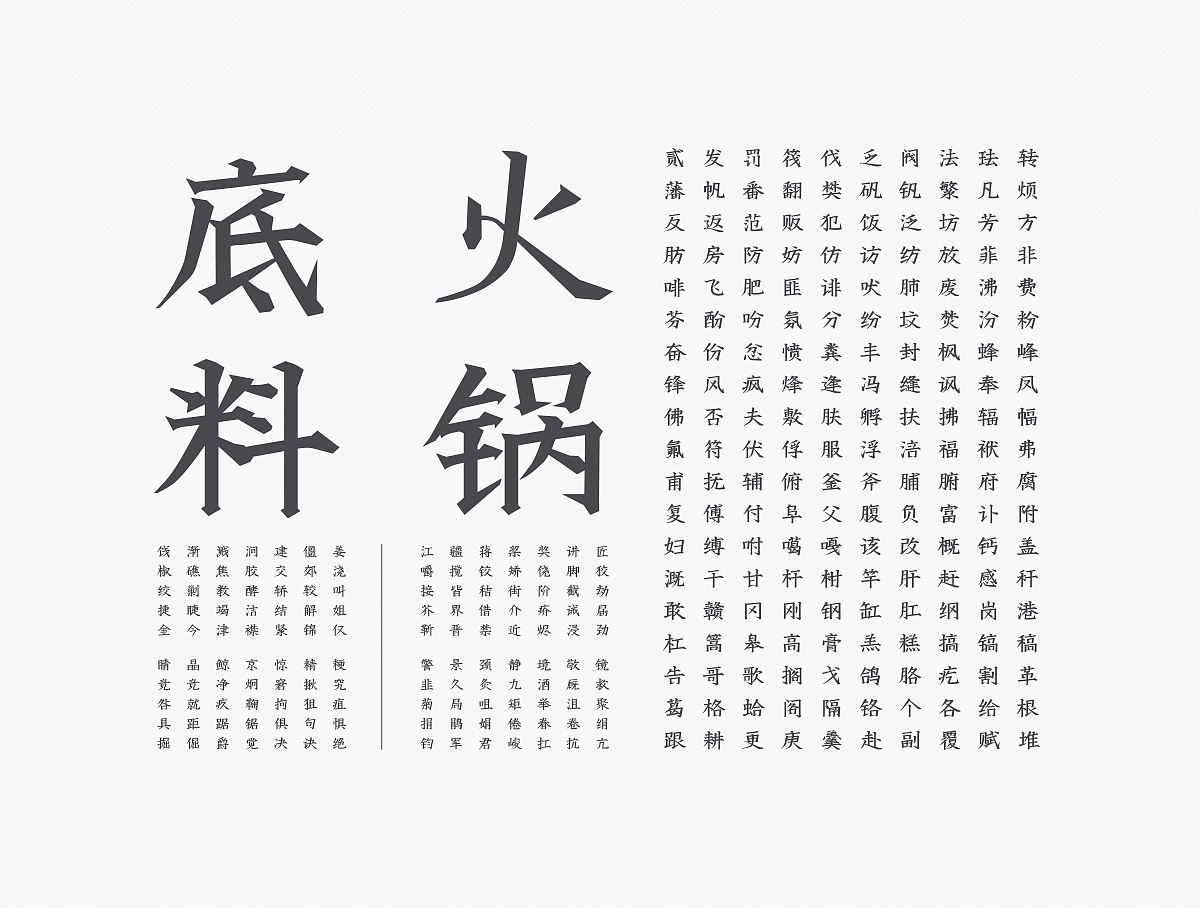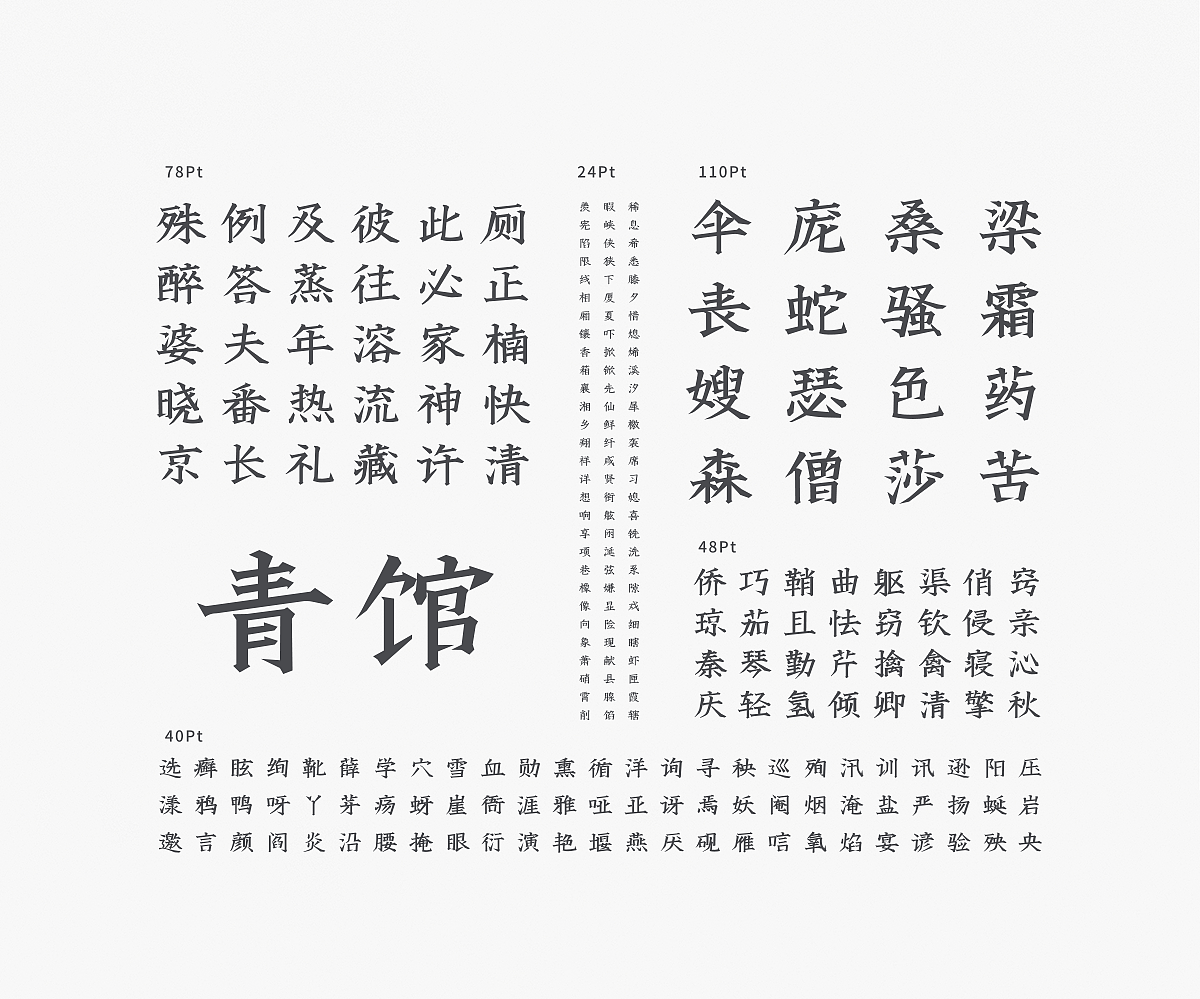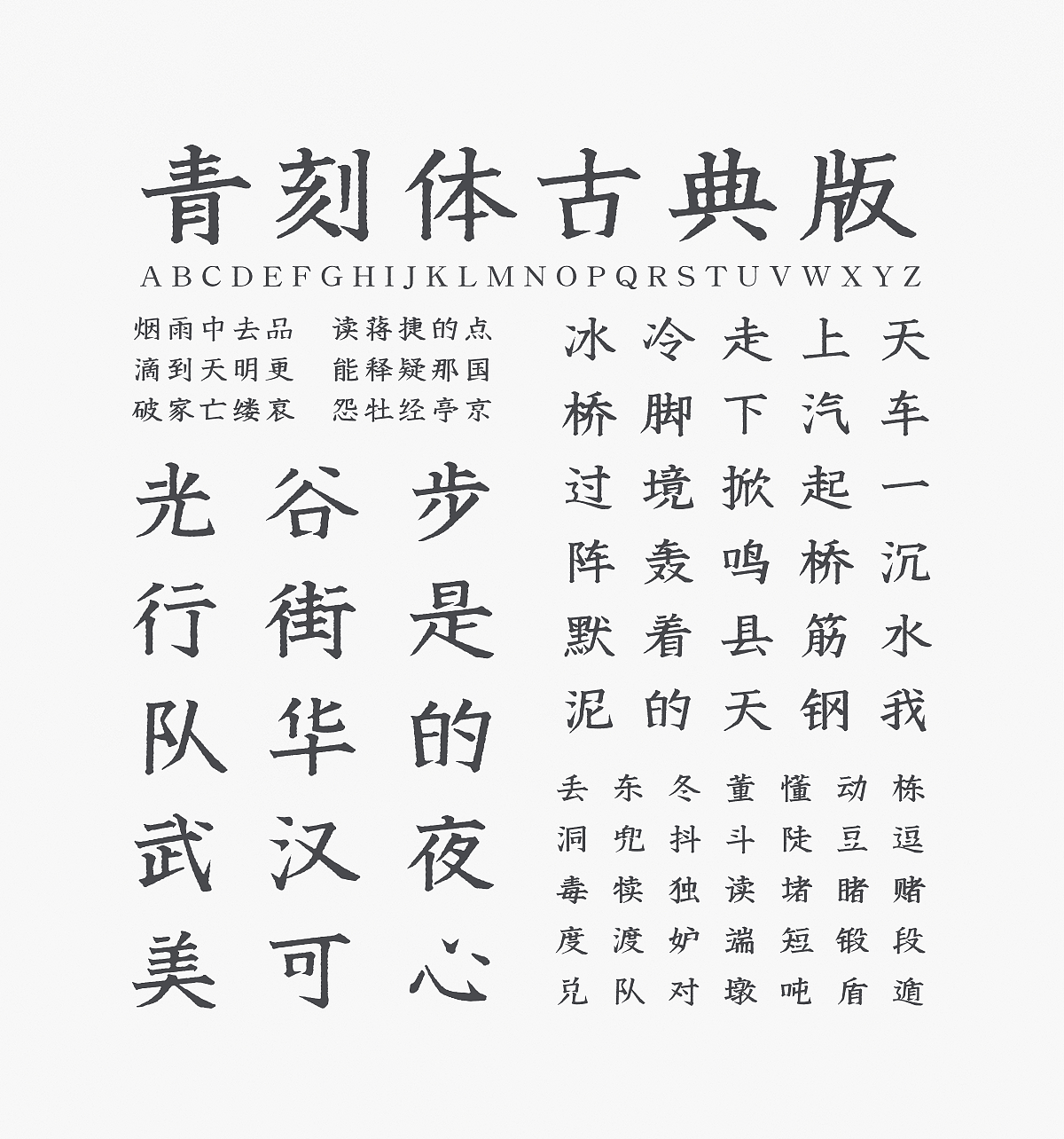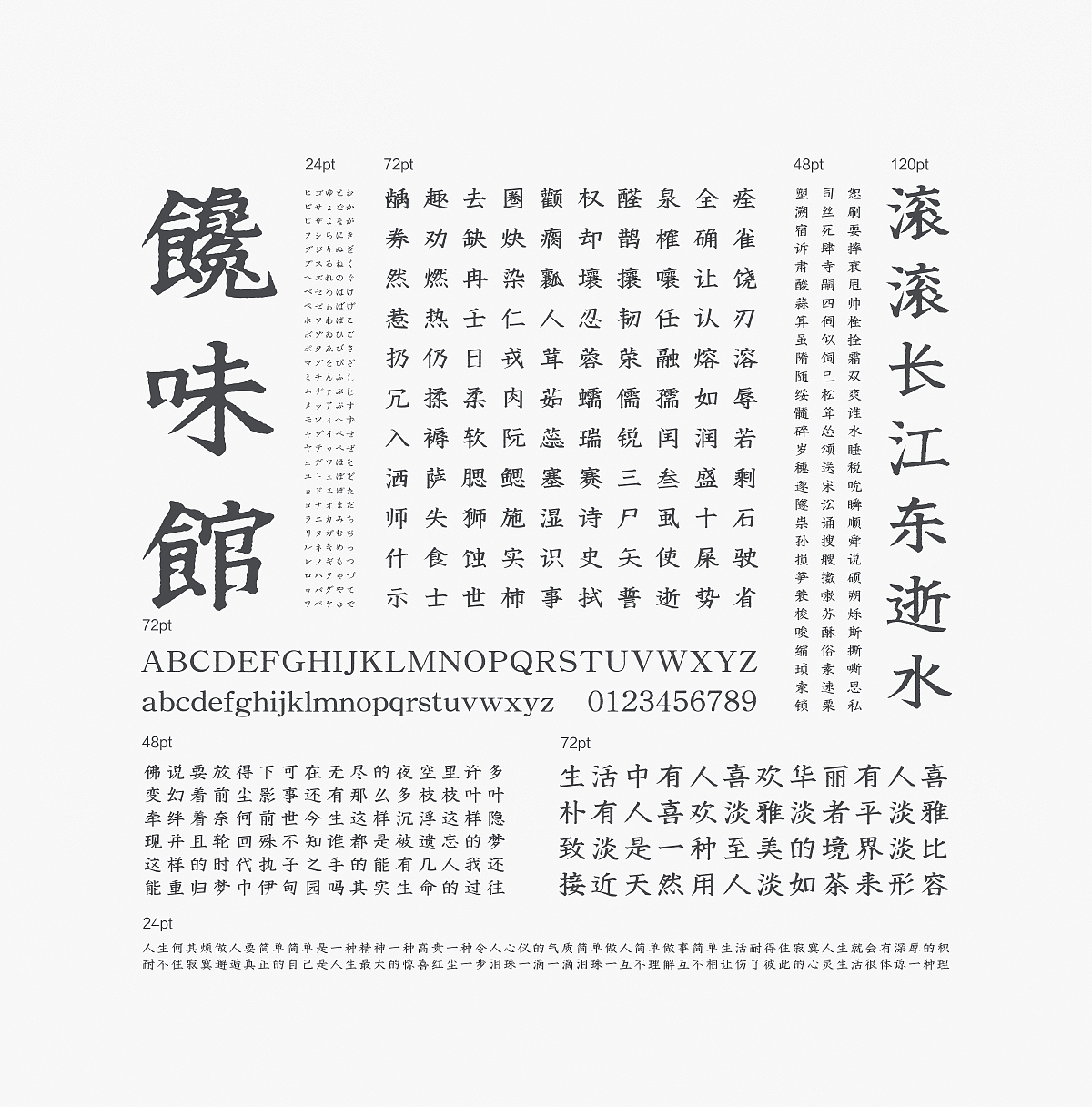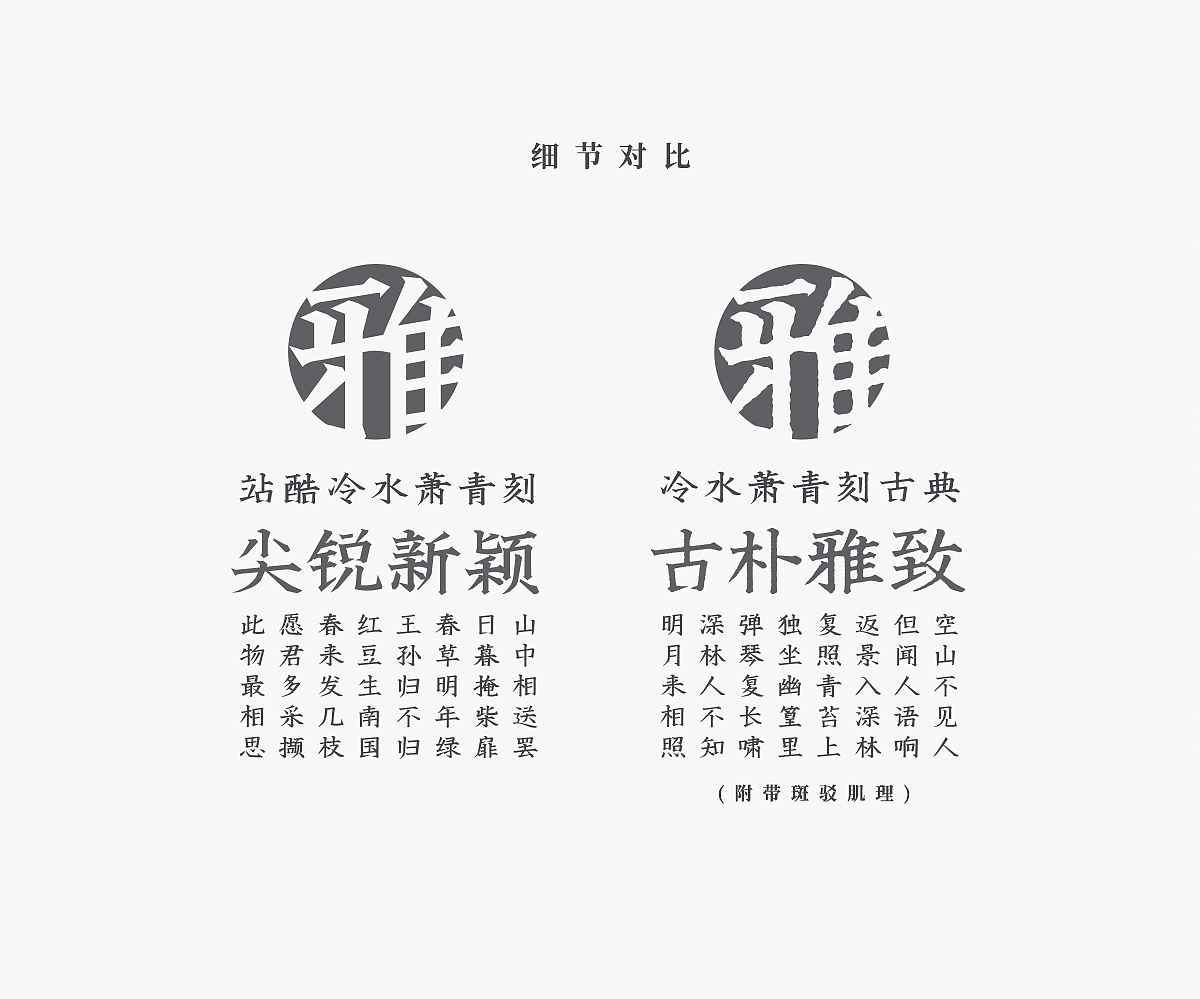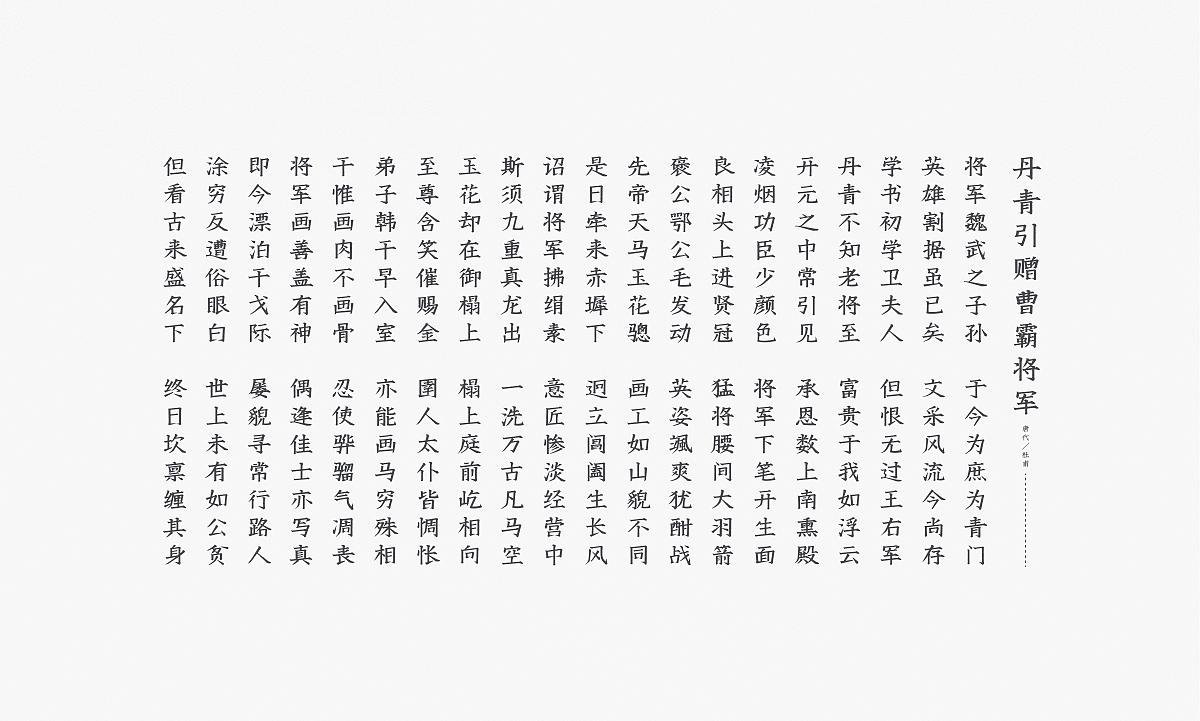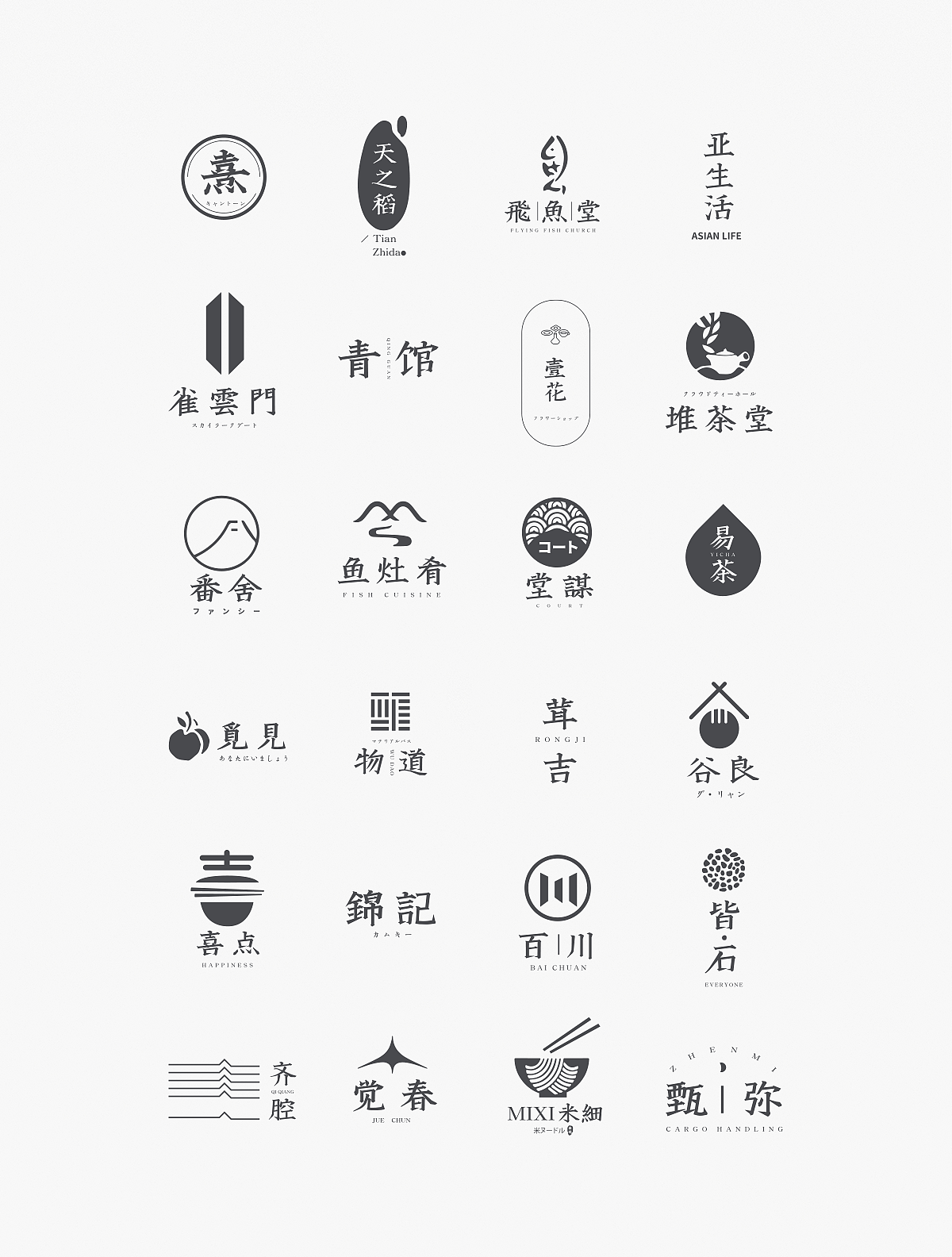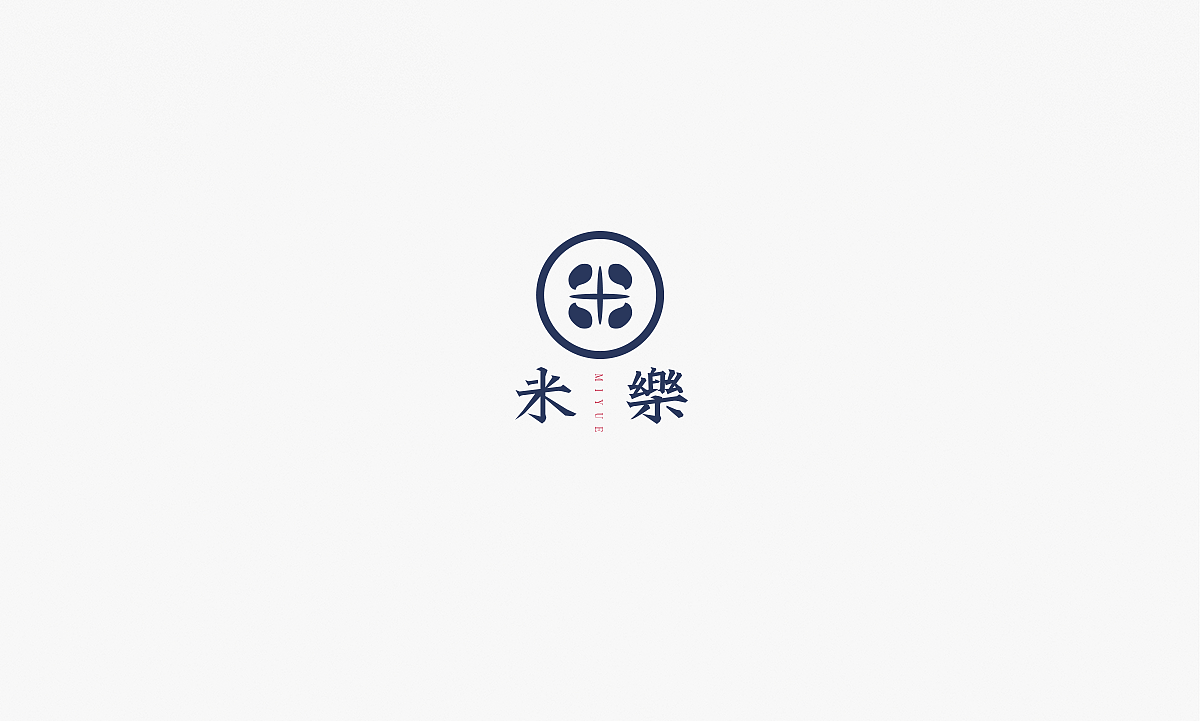
站酷冷水蕭青刻體 詳情頁
全套字庫簡繁體+日文+符號共計9913字
《站酷冷水蕭青刻體》區別于市面上大多數同類字體,是楷體字體的新型展示,在保留了傳統楷體的細節筆畫特點,運用新的表現形式,使字形筆畫結構具有清新、凌厲、干脆、舒服自然的字體性格特點,在筆畫與筆畫的銜接上也是保留了傳統的書寫習慣及特點,完成手寫與機打的結合,獨特的表現形式讓字體在商業應用中更加靈活和廣泛,能夠適合多種的商業場景,讓一個字體具有它的多面性,表現出它不一樣的字體性格。本款字形適用于個性類適合品牌標志、招牌、包裝、、廣告、游戲、中國風類設計等眾多場景應用。
當《站酷冷水蕭青刻體》完成測試中發現筆畫細節過于尖銳,故延展出一款斑駁質感的《站酷冷水蕭青刻古典體》供大家使用
站酷冷水蕭青刻體字形展示
站酷冷水蕭青刻體字號展示效果
站酷冷水蕭青刻古典體字形展示
站酷冷水蕭青刻古典體字號展示效果
兩款字庫筆畫細節對比
品牌標志、LOGO字體、招牌字體設計應用